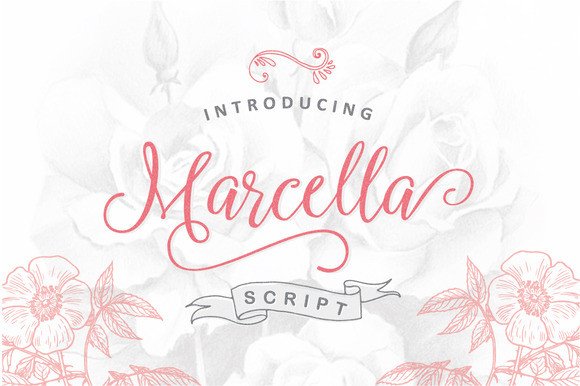
Marcella
Если вы ищете высококачественные ресурсы, такие как Marcella, этот премиум-пакет — фантастический выбор для ваших творческих проектов.
Создаете ли вы продукты POD (печать по требованию), свадебные приглашения или графику для социальных сетей, Marcella станет идеальным выбором.